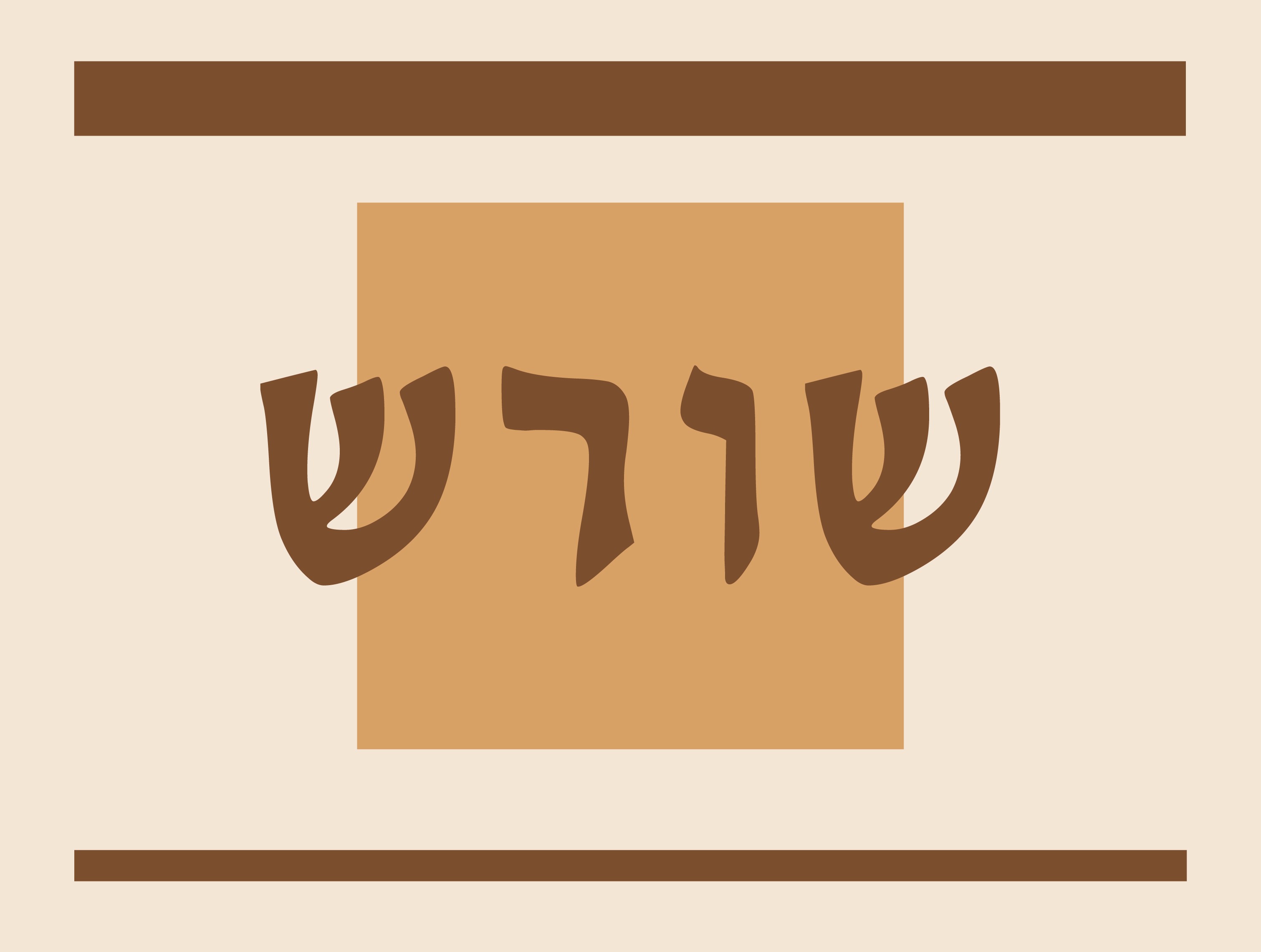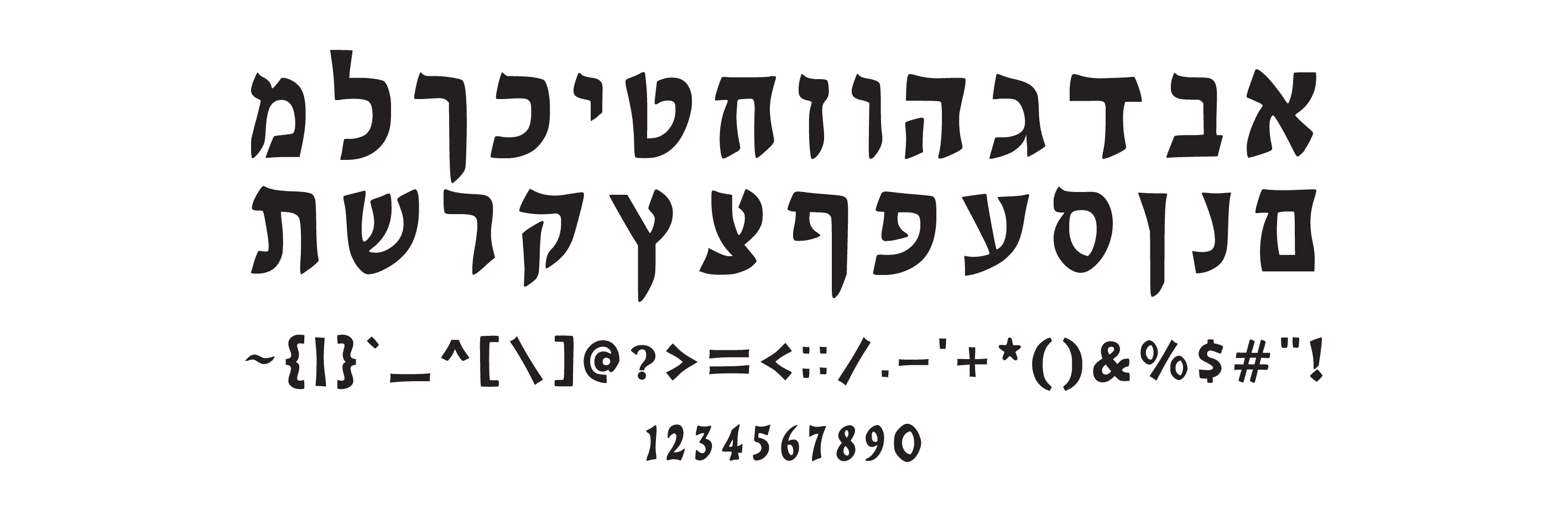
Root Font
Authentic and rooted Hebrew font, inspired by natural handwriting and local tradition.
שורש — פונט עם סיפור
אם אתה מחפש פונט שמביא איתו שורשים, מסורת וניחוח של אדמה — שורש כאן בשבילך.
זהו פונט שמבוסס על כתב יד חופשי אך יציב, עם קווים לא סימטריים במכוון, שמייצרים תחושת טבעיות ושורשיות עמוקה.
האותיות של שורש מספרות סיפור: הן חמות, מעט מחוספסות, עם מבנה אתני-מסורתי, שמתחבר למזרח התיכון, לכפריות, לאוכל אותנטי ולתרבות מקומית.
איפה הוא מרגיש בבית?
🫓 מסעדות מזרחיות ובתי אוכל אותנטיים
🍯 מיתוג למוצרים טבעיים בעבודת יד
🪴 חנויות בוטיק של טבע, חקלאות ושווקים
🎭 פסטיבלים מסורתיים ופרויקטים תרבותיים
למי הוא מתאים?
למי שמחפש פונט עם אופי — שורשי, אותנטי, חם ומחובר לאדמה, כזה שמדבר בשפה מקומית ומרגישה.